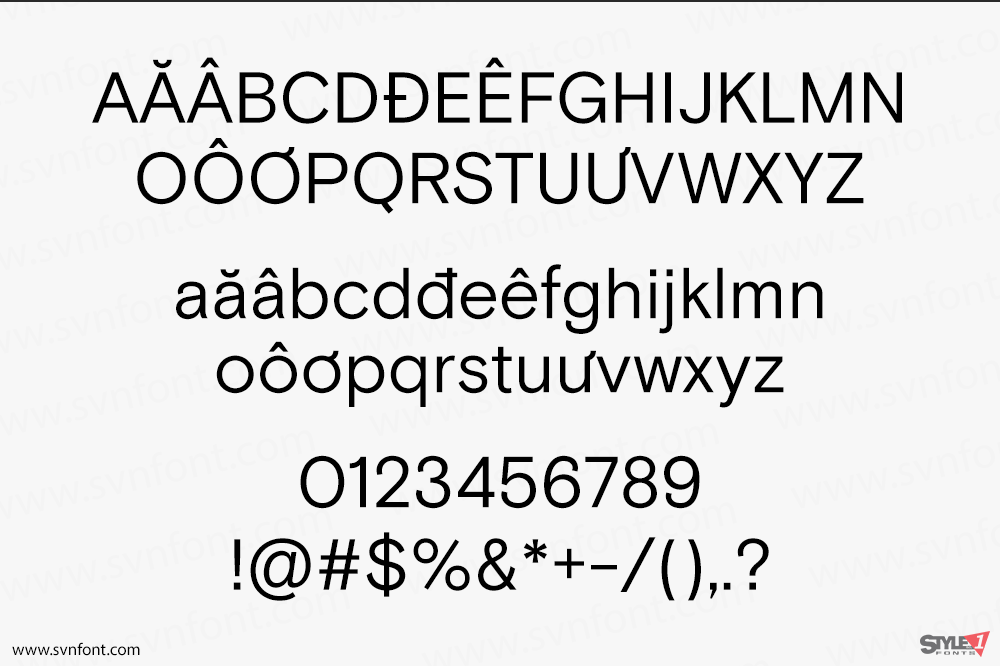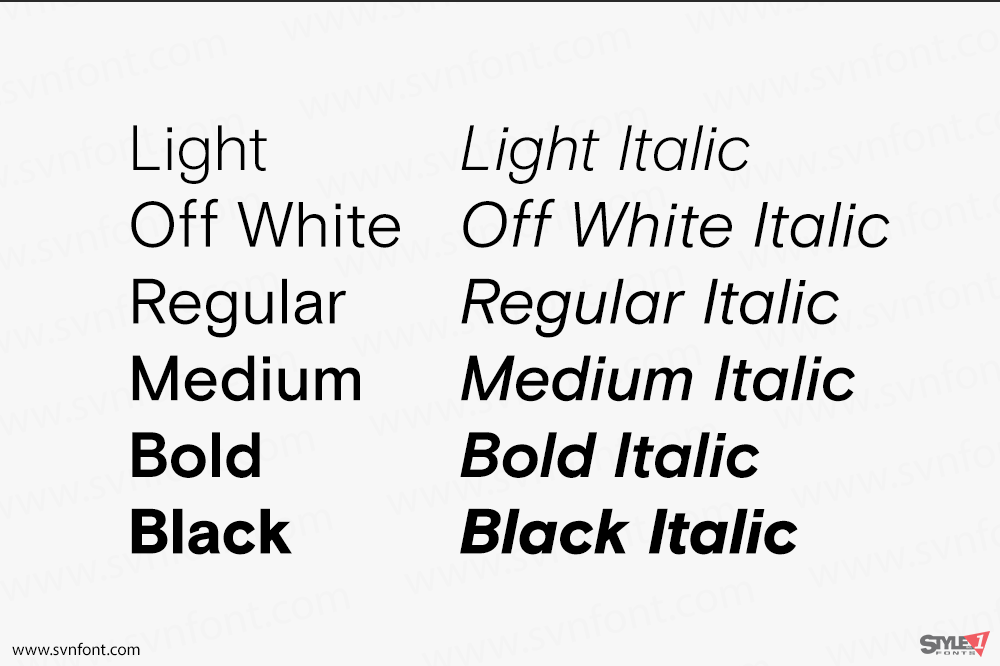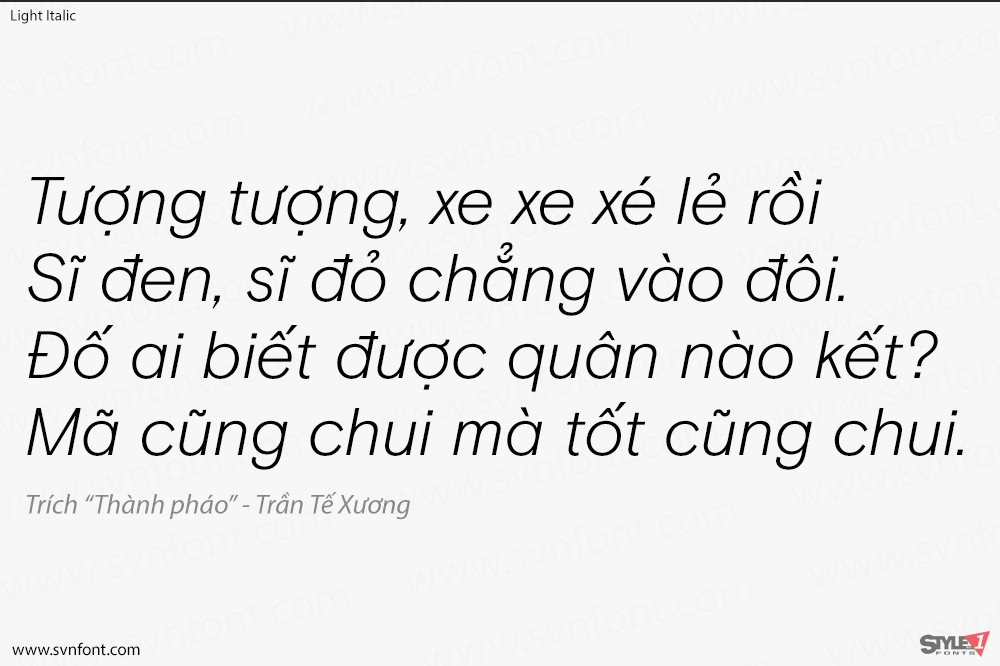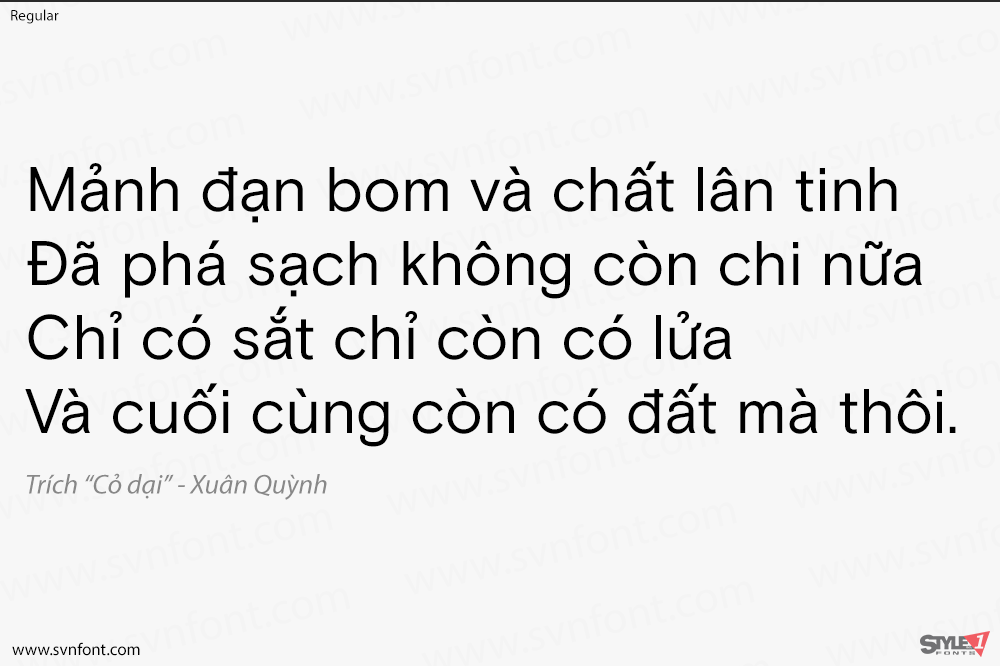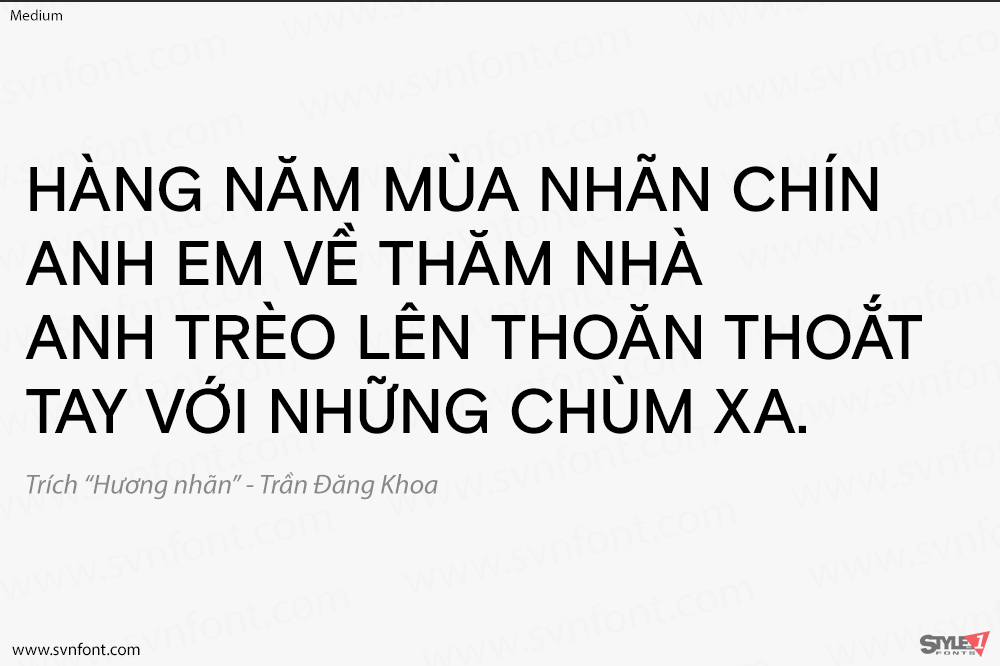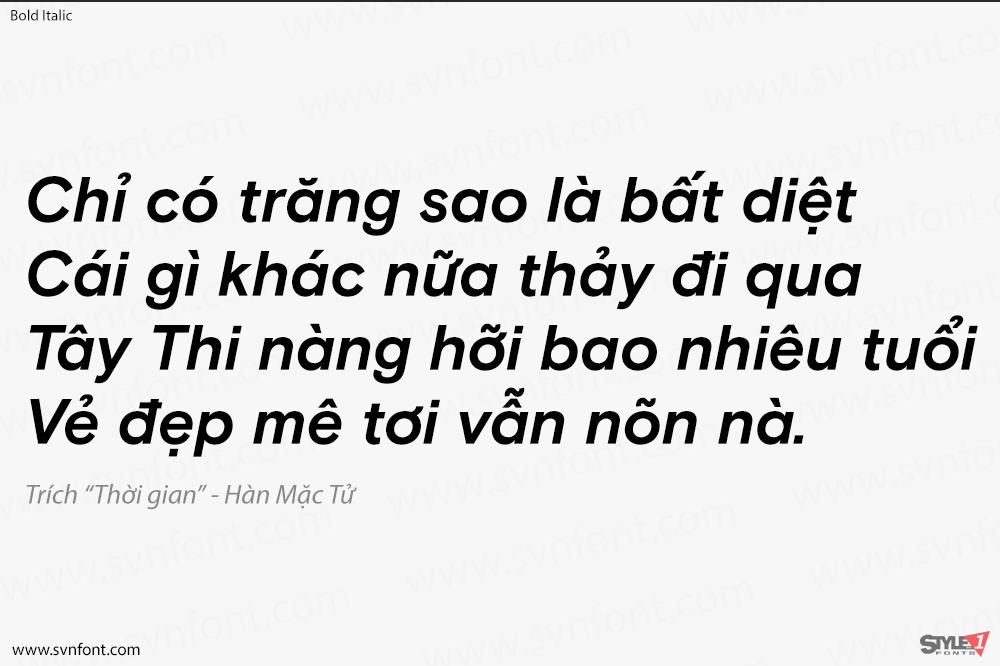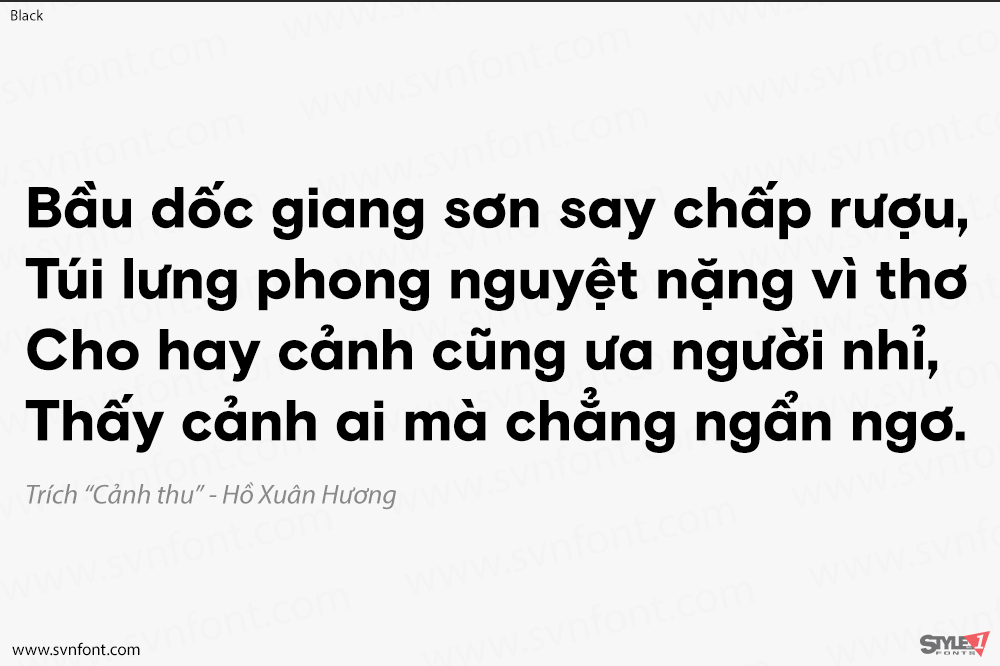
Ban đầu được vẽ ở độ đậm Regular cho việc tái thiết kế toàn diện tạp chí nhiếp ảnh HOTSHOE, chúng tôi vui mừng phát hành BASIS GROTESQUE ra thị trường, khoảng ba năm sau khi nó được hình thành lần đầu.
Trong suốt 36 tháng qua, chúng tôi đã tinh chỉnh và mở rộng kỹ lưỡng họ phông chữ này thành một “gia đình” 16 kiểu, và nhờ đó đã có cơ hội kiểm tra tất cả các phiên bản và phiên bản phụ của BASIS GROTESQUE trên vô số nền tảng, cả bản in và các định dạng khác.
Những điểm cảm hứng ban đầu – trong số đó có Akzidenz và các kiểu Grotesques đầu tiên từ Monotype – cuối cùng đã được từ bỏ nhưng vẫn được tôn vinh để tạo ra một thứ gì đó hơi “ngoan ngoãn” và có hình dáng đẹp hơn. Sự tương đồng về bộ xương có chủ ý giữa các độ đậm tạo ra một bộ sưu tập kiểu chữ thực sự đa dạng, từ Light đến Black với các kiểu in nghiêng tương ứng, và được bổ sung bởi các kiểu Monospaced ở cả độ đậm Regular và Bold (tất nhiên cũng có các kiểu in nghiêng đi kèm). Các tính năng OpenType phong phú và hỗ trợ cả chữ Kirin và tiếng Hy Lạp đều có sẵn trong tất cả các kiểu Pro.
Nhà thiết kế: The Entente
Nhà phát hành: Colophon Foundry